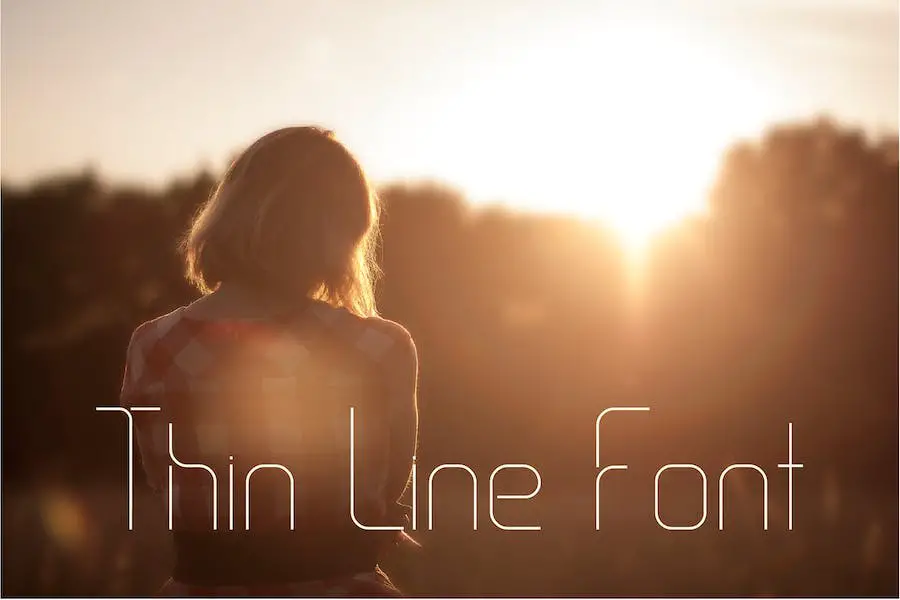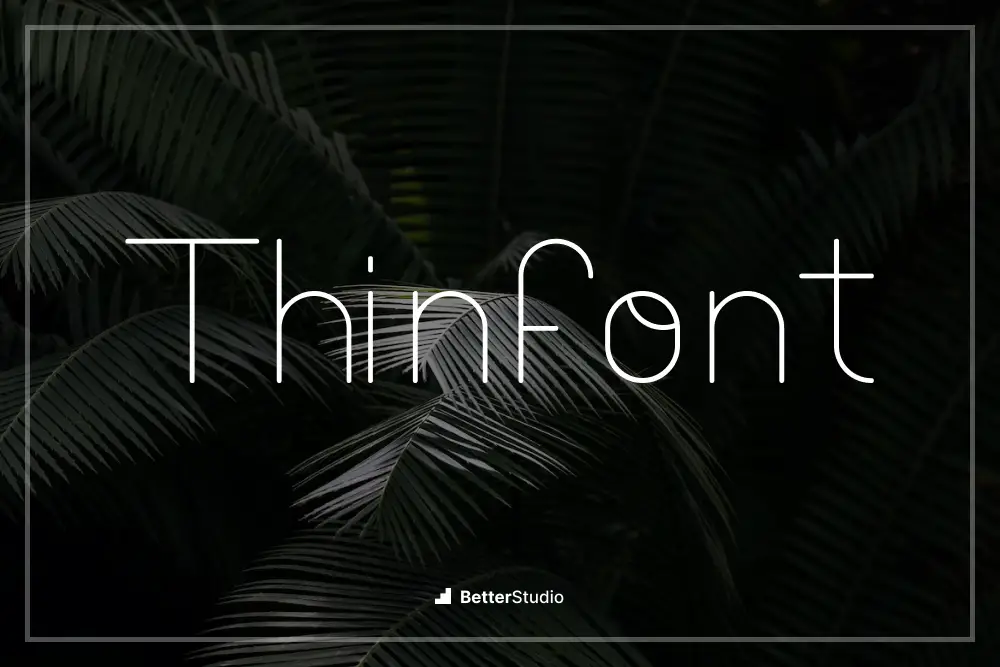
2023 年 34 种最佳细字体(免费和高级)
已发表: 2023-09-10您是一名平面设计师,正在寻找完美的细字体来提升您的设计项目吗? 别再犹豫了! 在这篇博文中,我们将分享 2023 年 34 种最佳细字体,包括免费和高级选项。
我们了解找到合适的字体来增强您的设计并使其脱颖而出的重要性。 加入我们,我们探索各种时尚和现代的细字体,这些字体将使您的项目更上一层楼。
在当今的数字时代,版式在创造具有视觉吸引力的设计方面发挥着至关重要的作用。 选择正确的字体可以决定一个项目的成败,而使用细字体可以增添一丝优雅和精致。
有如此多的选项可供选择,要决定哪些选项值得探索可能会让人不知所措。 因此,我们整理了 2023 年 34 种最佳细字体列表,以节省您的时间和精力。
现在,让我们深入研究这篇文章,发现各种可以激发和提升您的设计项目的细字体。
无论您是设计徽标、创建网站还是开展品牌项目,这些字体都一定能为您提供所需的多功能性和视觉冲击力。 那么,让我们开始一起探索细字体的世界吧!
最佳优质细字体
希望为您的设计增添一些优雅和精致? 我们精选的最佳优质细字体就是您的最佳选择。 这些字体将使您的项目更上一层楼,所以不要错过 - 立即查看!
戈尔多尼
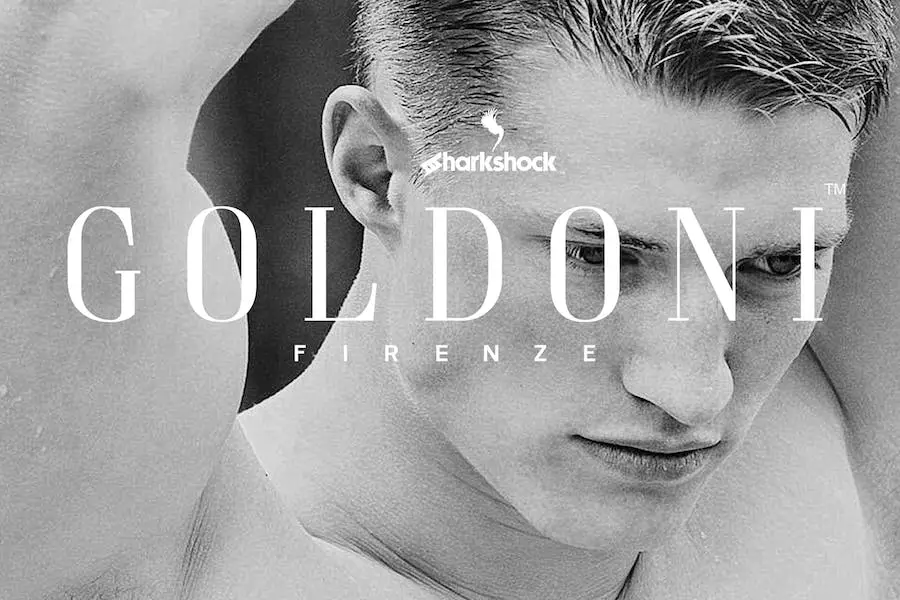
Goldoni 是一款散发着意大利奢华气息的精美字体。 凭借其简单而优雅的设计,这款标题衬线字体为任何项目增添了一抹精致。 该字体具有垂直强调和经典、超干净的外观,与宽大的间距和细长的字体形成美丽的对比。
无论您需要豪华的标志、引人注目的报纸展示、迷人的标题还是迷人的电影海报,Goldoni 都是完美的选择。 它包含基本和扩展的拉丁字符、数字、标点符号、欧洲口音、变音符号、替代符号和完美的字距调整。
凭借其自由的间距和细小的字符,Goldoni 创造了令人惊叹的视觉效果,强调了负空间的美感。
富加特薄
Fulgate Thin 是一款奢华字体,可为您的设计项目带来夏季主题的宣传。 当您正在寻找细、窄或浅字体来增强您的创作时,它是完美的选择。
借助 OpenType 功能,Fulgate 提供了独特的选项,例如 Capital Swash,它会在第一个字母大写时替换它。 此字体还包括小型大写字母,用于具有大写高度的小写形状。
为了增加多功能性,小写字符有其他选择,可以保持奢华感而不变得混乱。 该字体甚至包括数字字符的特殊功能,如序数、下标、上标和分数。 告别无聊的字体,让 Fulgate Thin 提升您的设计。
繁花似锦
Flowery 是一款出色的字体,无疑会增强您的图形设计项目。 此字体属于细字体类别,也称为“细字体”、“窄字体”或“浅字体”。 它为您的设计提供简约时尚的外观。
The Flowery 的多功能性令人印象深刻。 它非常适合各种项目,从专业文档到引人注目的图形。 无论您的网站、博客还是社交媒体帖子需要字体,这种字体都会让您的文本脱颖而出。
格林诺德
Greenold 是一种现代细衬线字体,有大写和小写字母,提供 OTF 和 TTF 文件。 凭借其时尚优雅的设计,它为任何平面设计项目增添了一丝精致感。
它还包括数字和标点符号,使其能够满足各种创意需求。 对于想要通过时尚精致的字体增强项目视觉吸引力的图形设计师来说,Greenold 字体是完美的选择。
拉斐拉
Rafaela 是一种独特的显示字体,可为任何设计项目增添一丝优雅。 凭借其细衬线风格,它在其他字体中脱颖而出。 它提供小写和大写选项,使其适用于各种创意活动。
克利奥迪斯
Cleodays 是一种无衬线字体,提供各种替代字体和连字,让您可以自由地创建令人惊叹的版式设计。
借助 Cleodays,您可以灵活地组合不同的字符和连字,为您的项目实现完美的外观。 无论您想要创建时尚现代的设计还是更优雅精致的风格,这款字体都能满足您的需求。
它旨在提升您作品的视觉吸引力并增添专业性和创造力。
治愈术
Curefancy 是一种优雅的细衬线字体,非常适合希望增强项目设计的图形设计师。 凭借其时尚和精致的吸引力,这种字体一定会给任何设计带来一丝优雅的感觉。
它提供了广泛的功能,包括数字和标点符号,以及小写和大写变体。 无论您是在制作徽标、网站设计还是印刷材料,Curefancy 都是一种可以将您的项目提升到新水平的字体。
维多利亚
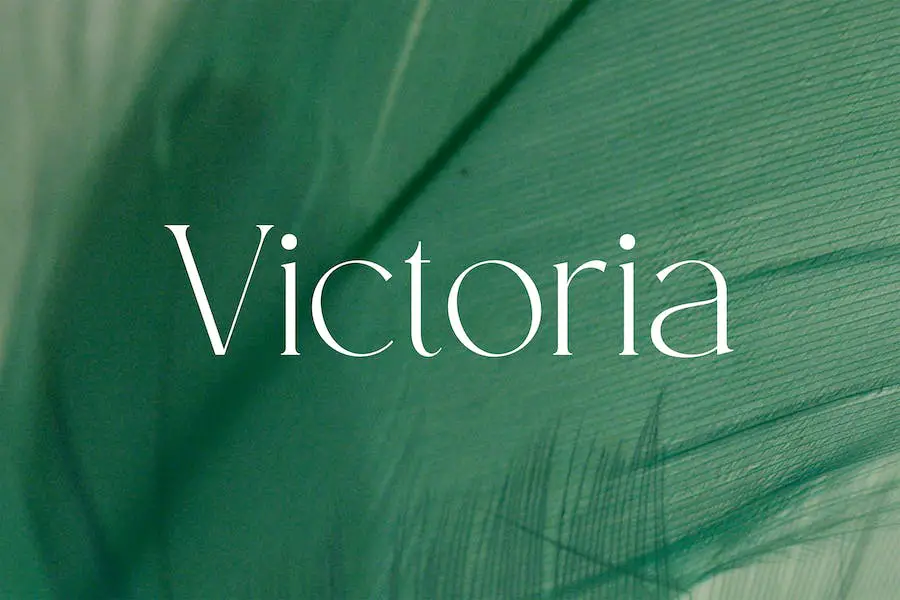
Victoria 是一种现代细衬线时尚字体,可为任何设计项目增添一丝优雅和精致。 该字体以其流畅的线条和精致的曲线增强了整体美感和视觉吸引力。
无论您是在制作徽标、品牌材料还是网站,Victoria 都是希望将项目提升到新水平的平面设计师的完美选择。
维多利亚纤细优雅的笔触赋予其精致时尚的外观,非常适合时尚相关设计或任何需要品味的东西。
阿格莫薄
Agemo Thin 是一种现代几何字体,专为品牌、标题和其他出色的排版需求而创建。 这种字体提供了额外的替代样式,使您的设计更令人难忘。
它非常适合添加风格并为业务、最新技术、操作和简约主题创建标题概述。 凭借其简约风格和现代感,Agemo Thin 可以让您在您承担的任何项目中释放您的创造力并展示您的主要想法。
特罗韦洛
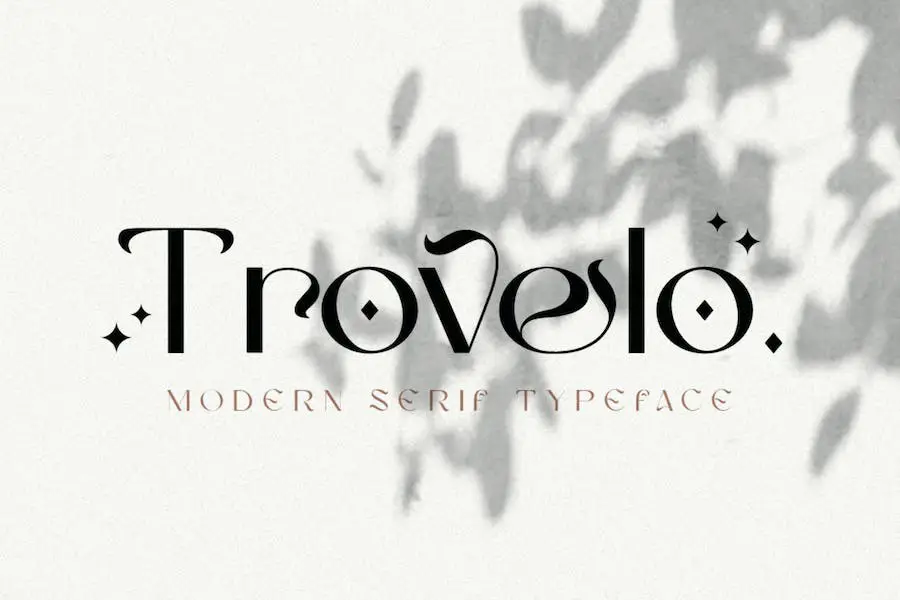
希望将您的平面设计项目提升到一个新的水平? Trovelo 是您的最佳选择,It Serif Thin 字体。 该脚本集合专为个人品牌设计,但其多功能性使其成为各种应用程序的完美选择。
无论您需要用于个人品牌、徽标、姓名标签、手写报价、产品包装、商品、社交媒体帖子、贺卡、摄影签名还是广告的字体,Trovelo 都能满足您的需求。
凭借其大胆的标志性风格,该字体系列将为任何设计增添一丝优雅和专业精神。
嘿,明白了
Hey Gotcha 字体是一种多功能字体,提供多种样式,包括粗体、细体和阴影层。 它非常适合为您的设计增添俏皮和有趣的感觉,尤其是那些专为儿童设计的设计。
凭借其手工制作的字体外观,这种字体一定会吸引注意力并激发您项目的创造力。 无论您是从事广告活动的平面设计师还是为儿童读物创作插图,Hey Gotcha 字体都是您工具包中的必备品。
其大胆和纤薄的变化让您可以尝试不同的风格并创造出引人注目的设计。 将其与鲜艳的色彩和异想天开的插图搭配,真正让您的项目脱颖而出。
诺里斯
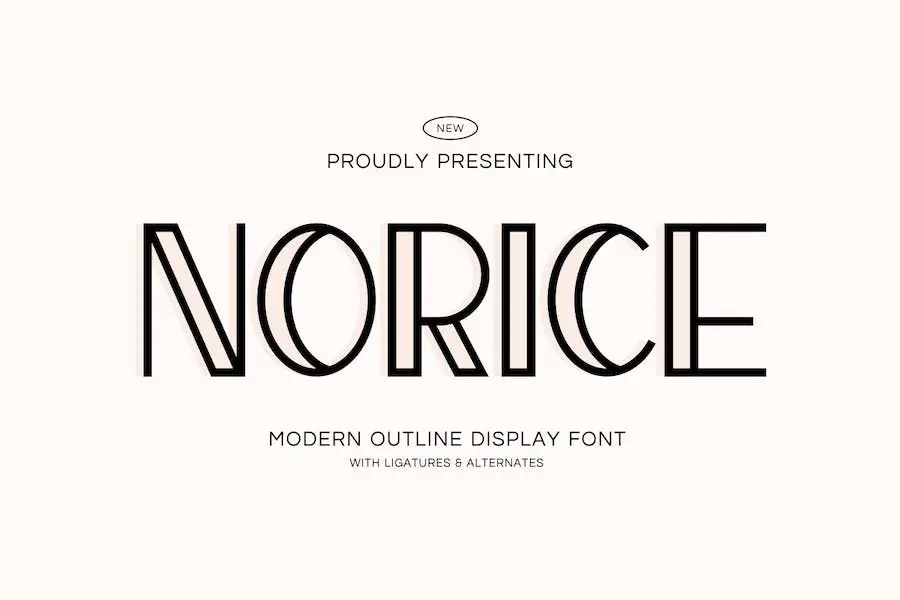
Norice 是一种多功能字体,非常适合各种设计项目。 无论您是在制作邀请函、徽标、品牌、杂志还是产品包装,这种字体一定会给您的项目带来优雅和精致的感觉。
Norice 的与众不同之处在于它能够在大尺寸和小尺寸下无缝工作。 无论您的设计规模如何,该字体都将保持其清晰度和可读性,确保您的信息响亮而清晰。
Norice 凭借其纤薄、现代的设计,散发出优雅的视觉效果。 平滑的曲线和美丽的连线为您的作品增添了额外的精致度,使其真正吸引眼球。
周日阳光
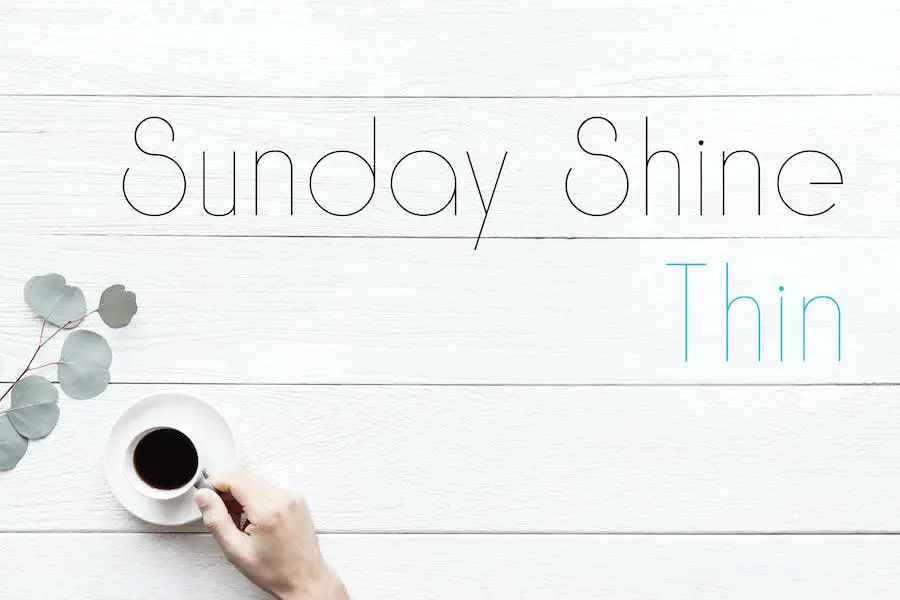
Sunday Shine 是一种全新的几何显示字体,被称为 It 字体系列的瘦版。 它是各种项目的完美选择,包括企业设计、商业材料、广告、户外标牌、邀请函等。
Sunday Shine 为任何设计增添了一丝优雅和精致,使其成为希望增强其项目的图形设计师的必备工具。
一根细线
One Thin Line 是一种令人惊叹的字体,可为任何设计项目增添一丝优雅和简约。 其简约风格是通过仅使用一根线来形成每个字母和字符来创建的。
查看屏幕截图,了解所有可用角色。 使用 One Thin Line,您可以轻松实现干净、现代的外观,从而增强项目的整体设计。 尝试一下,将您的设计提升到一个新的水平! 祝你有美好的一天!
胆汁
CHOLE – 一款时尚的字体,可将您的设计项目提升到一个新的水平。 凭借其纤细、优雅的线条,它为任何图形设计增添了一丝精致感。
无论您是在制作徽标、T 恤印刷还是任何品牌项目,CHOLE 都是让您的设计脱颖而出的完美选择。 其多功能性使其适合各种环境,并确保您的创作看起来非常出色。
使用 CHOLE 为您的设计增添现代而真实的触感——这是希望提升项目水平的平面设计师的终极字体。
西恩特罗
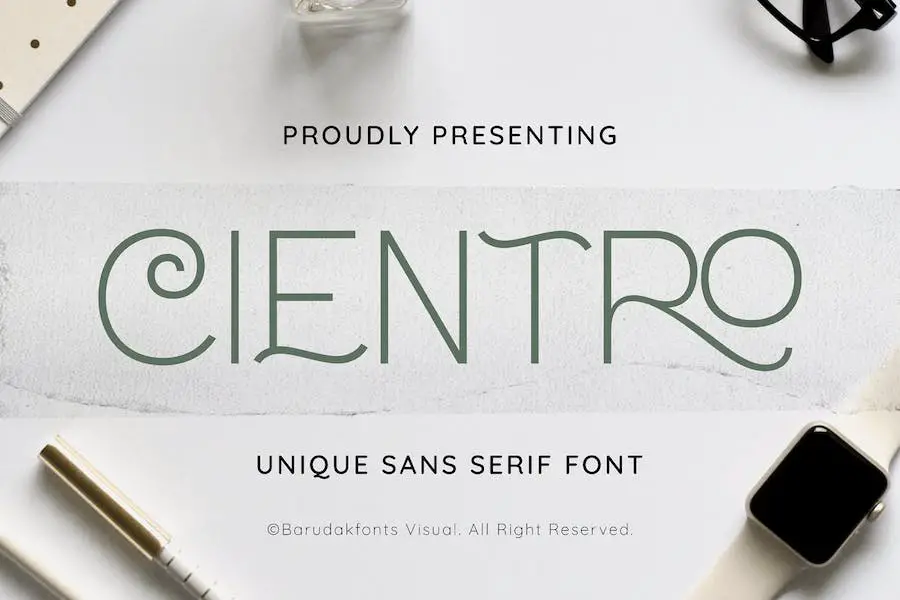
Cientro 是一款时尚的 Serif Thin 显示字体,非常适合希望增强其项目的图形设计师。
凭借其创造性的多功能性,您可以轻松地在各种设计元素上编辑和使用此字体,例如商品、徽标、贴纸设计、补丁、徽章等。
其简洁优雅的设计为任何项目增添了一丝精致感,使其成为寻求提升工作水平的设计师的必备工具。 无论您从事品牌、包装还是任何其他设计项目,Cientro 一定会以其现代和专业的美学给您留下深刻的印象。
夏令
隆重推出 Summertime,这是一款纤细的休闲手写字体,非常适合您的所有设计需求。
无论您是在制作婚礼请柬、夏季场合、贺卡、海报、明信片、摄影、品牌、社论还是签名,这种字体一定会增强您的项目。
Summertime 以其休闲而温馨的风格为您的设计增添个人风格。 那为什么还要等呢? 立即下载,让您的项目更上一层楼!
金德斯
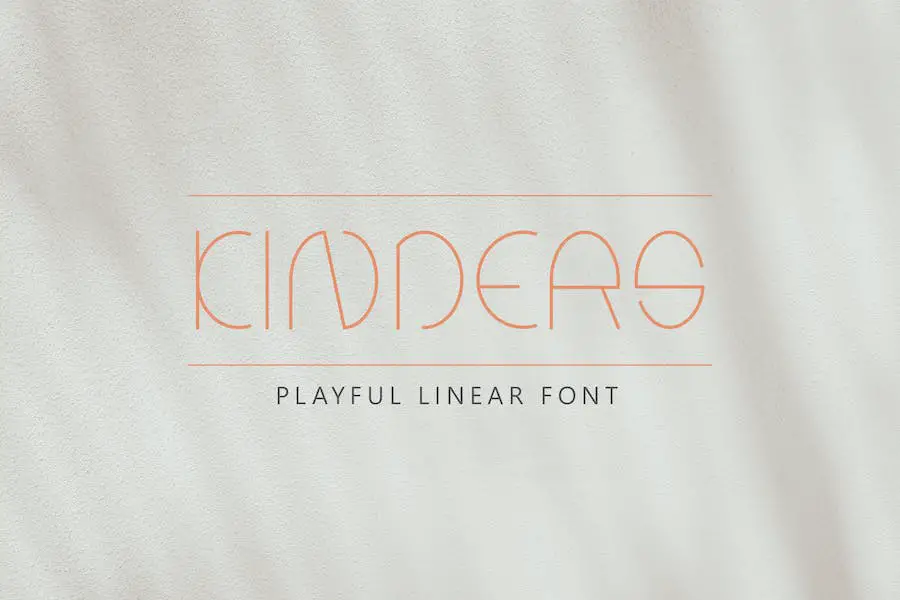
“Kinders 是一款细线性字体,每个字母都散发着优雅的气息。 这种现代而时尚的字体不仅引人注目,而且非常易于使用。 无论您是设计海报、徽标、T 恤、标题、传单,甚至是 CD 封面,Kinders Font 都是完美的选择。
它也非常适合引用、名片、品牌、杂志、社交媒体、广告、产品设计以及任何需要现代或未来外观的内容。 凭借其时尚的设计和可读性,Kinders 在任何专业设计项目中真正脱颖而出。
珍珠
Pearls 是一种美丽的细 Sans 字体,散发着优雅和现代气息。 对于希望为他们的项目增添优雅和时尚风格的图形设计师来说,它是完美的选择。
无论是创建引人注目的网站、设计迷人的徽标,还是制作视觉上令人惊叹的杂志传播或社交媒体图形,Pearls 都能满足您的需求。
凭借其时尚而精致的美感,Pearls 可立即升级任何项目的整体设计。 其现代而优雅的特性使其成为各种设计应用的多功能选择。
尤尼斯·尤尼索德
Ones Unisod 是一种适合各种行业的字体,从个人项目到公司设置。 无论大小如何,这种字体都可以完美适应大型和小型设计,使其具有令人难以置信的多功能性。
无论您是在创建徽标、邀请函、杂志布局,甚至是产品包装,该字体都以其流畅的线条和优雅的连字增添了一丝精致感。 Ones Unisod 具有清晰且有吸引力的吸引力,您的作品将显得精致且迷人。
克利奥迪斯
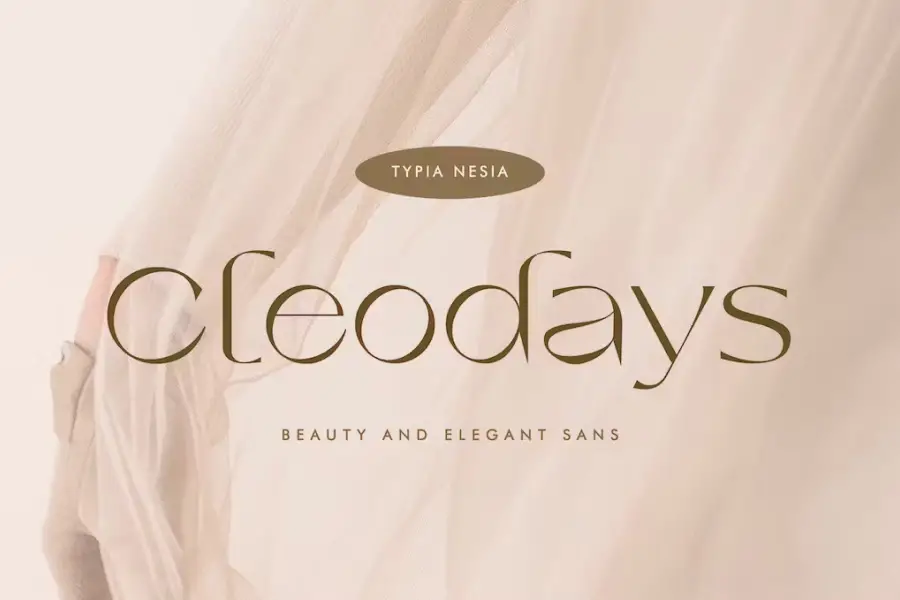
Cleodays 是一种无衬线字体,提供替代字体和连字,以创建独特且时尚的版式设计。
它非常适合奢侈品标志、编辑设计、化妆品、时尚、艺术、文具、博客等各种项目。 您可以将它用于任何创造性的尝试,以增添一丝精致感。
贝弗拉尔
Bepholar 是一款时尚的字体,非常适合希望增强其项目的图形设计师。 It Font – 现代字体,正如它的正式名称一样,是一种大胆而真实的显示字体,可为任何设计带来现代气息。
细字体是指设计纤细或精致、笔划细的字体。 这些字体因其优雅和现代的外观而经常被使用。 它们是标题、标题或任何需要时尚简约风格的设计的绝佳选择。
细字体可以为您的设计增添一丝精致和精致。 它们在现代和简约主题中表现良好,呈现出时尚干净的外观。
细字体可以使您的文字脱颖而出并营造出优雅的感觉。 然而,在正文中使用细字体时,考虑易读性很重要,因为它们在较小的尺寸下可能更难以阅读。
结论
为了总结本文,我们探索了 2023 年 34 种最佳细字体,范围从免费到高级选项。
我们讨论了选择正确字体来增强图形设计项目的重要性,以及这些细字体如何为您的设计带来时尚和优雅的触感。